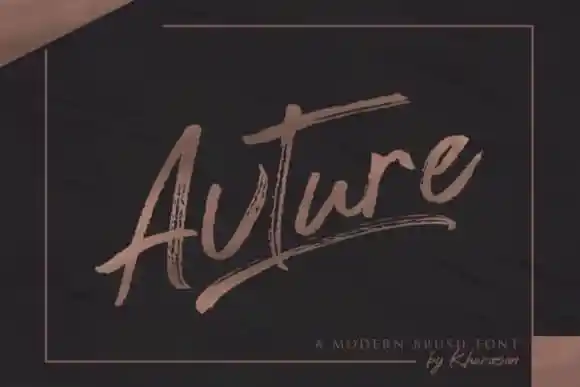
Avture Brush Font – Download Grátis
Avture Brush Font é uma elegante fonte escrita a mão projetada para combinar perfeitamente com as demandas do design de marcas e logotipos. Essa font apresenta um estilo único, trazendo um ar despojado e natural aos seus trabalhos futuros. Criada pelo designer Khurasan no site 99designs, Avture Brush é uma font excepcionalmente criativa, meticulosamente desenvolvida para se tornar uma favorita entre designers de todo o mundo. Preserva a influência sofisticada da caligrafia enquanto mantém um tom contemporâneo e moderno. Descubra esse charme inconfundível em Avture Brush; ele vai transformar sua próxima peça visual em algo extraordinário, elevando seu projeto a novos níveis de beleza e originalidade.